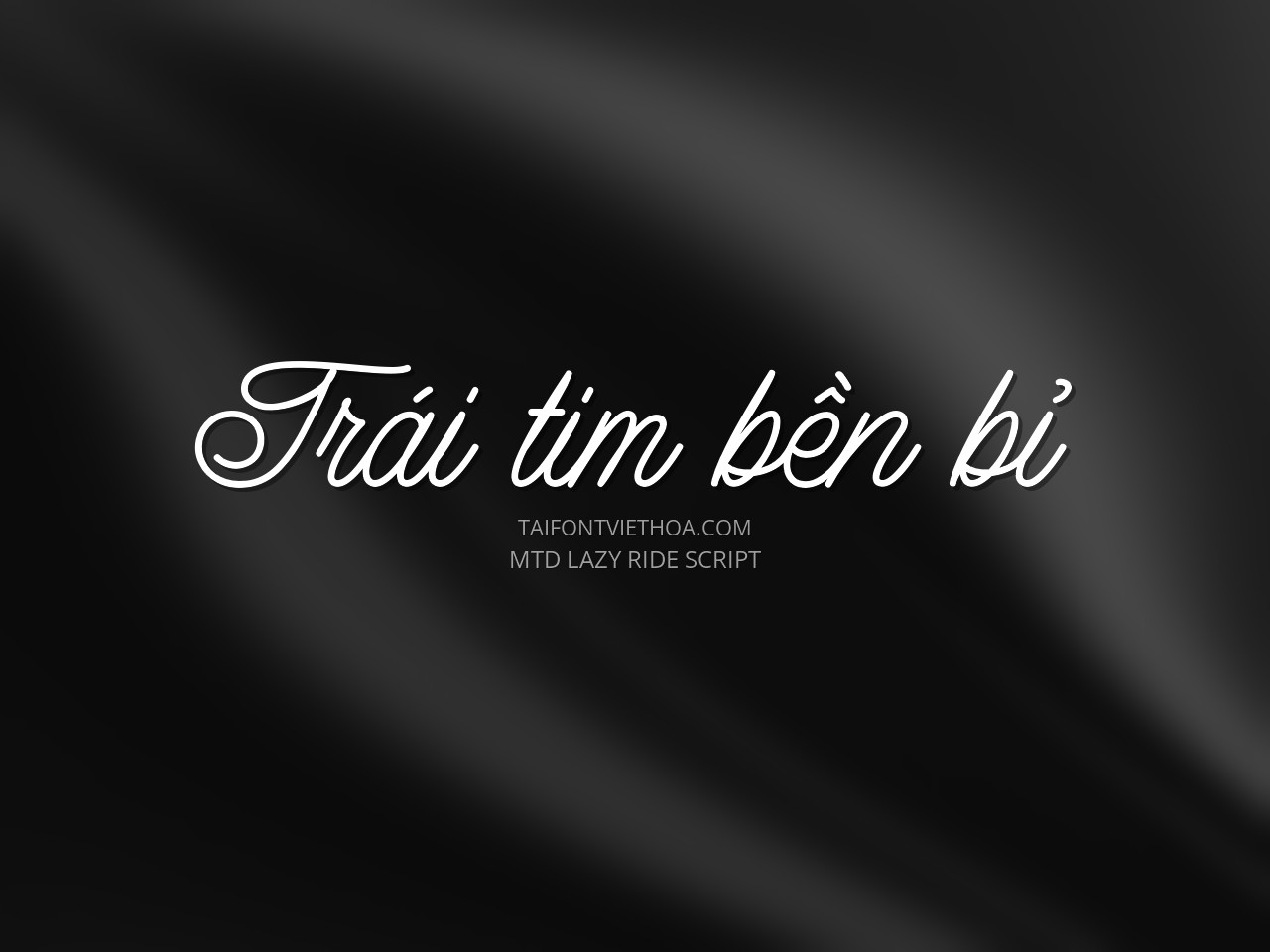
Font việt hóa MTD Lazy Ride Script
Tác giả Font: Hendra Pratama
Giới thiệu về font Lazy Ride Script
Lazy Ride Script là một font viết tay mang phong cách thư giãn, tự nhiên và phóng khoáng, được thiết kế bởi Motokiwo Type (MTD). Font mô phỏng những nét viết tay nhanh, hơi nghiêng, với cấu trúc chữ mềm mại và liền mạch. Sự “lười biếng” trong cái tên không phải là thiếu tinh tế, mà chính là biểu hiện của sự thoải mái, tự do, đầy sáng tạo. Phiên bản Việt hóa do chính MTD thực hiện, hỗ trợ trọn bộ ký tự tiếng Việt cùng hơn 70 ngôn ngữ khác, giúp font dễ dàng ứng dụng trong các dự án đa quốc gia hoặc truyền thông số toàn cầu.
Font Lazy Ride Script được taifontviethoa.com chọn lọc kỹ càng và đưa vào nhóm font viết tay nghệ thuật. Với tính cách cá nhân rõ rệt và sự bay bổng trong từng nét chữ, font này mang đến cảm giác gần gũi, tự nhiên nhưng vẫn thể hiện được tính thẩm mỹ cao trong thiết kế đồ họa hiện đại.
Đặc điểm thiết kế và ứng dụng của font Lazy Ride Script
Font nổi bật với những đường nét viết tay liền mạch, hơi nghiêng nhẹ, độ tương phản thấp giữa các nét đậm – mảnh, tạo cảm giác chân thực như chữ viết tay thực tế. Các ký tự có độ giãn thoáng, khoảng cách ổn định, giúp nội dung trở nên thoải mái, nhẹ nhàng khi trình bày. Bộ ký tự đi kèm với nhiều ligatures và alternates hỗ trợ thiết kế linh hoạt.
Ứng dụng phù hợp: typography trang trí, tiêu đề blog cá nhân, logo thương hiệu cá tính, thiệp mời phong cách casual, bài đăng mạng xã hội, bao bì sản phẩm handmade hoặc các thiết kế hướng đến sự tự nhiên, sáng tạo. Ngành nghề phù hợp: thời trang, lifestyle, thiết kế nội dung cá nhân hóa, đồ thủ công, quảng cáo nghệ thuật và truyền thông thương hiệu cá nhân.